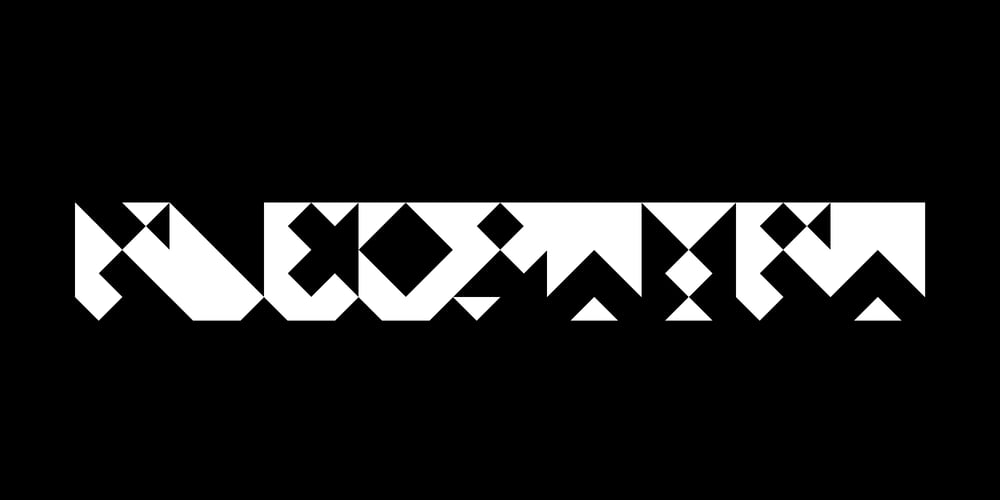
Kleopatra Font Family was designed by Luis Rutz and published by Luis Rutz. Kleopatra contains 1 styles and family package options. Futuristische Zeichen aus einer anderen Zeit. Hervorgebracht aus dem Sand von Memphis, 18 Kilometer südlich von Kairo. Gesammelt und rekonstruiert von deutschen Architekten, treu einer kompromisslosen Geometrie, die jemanden zu repräsentieren scheint, der sehr viel moderner ist.